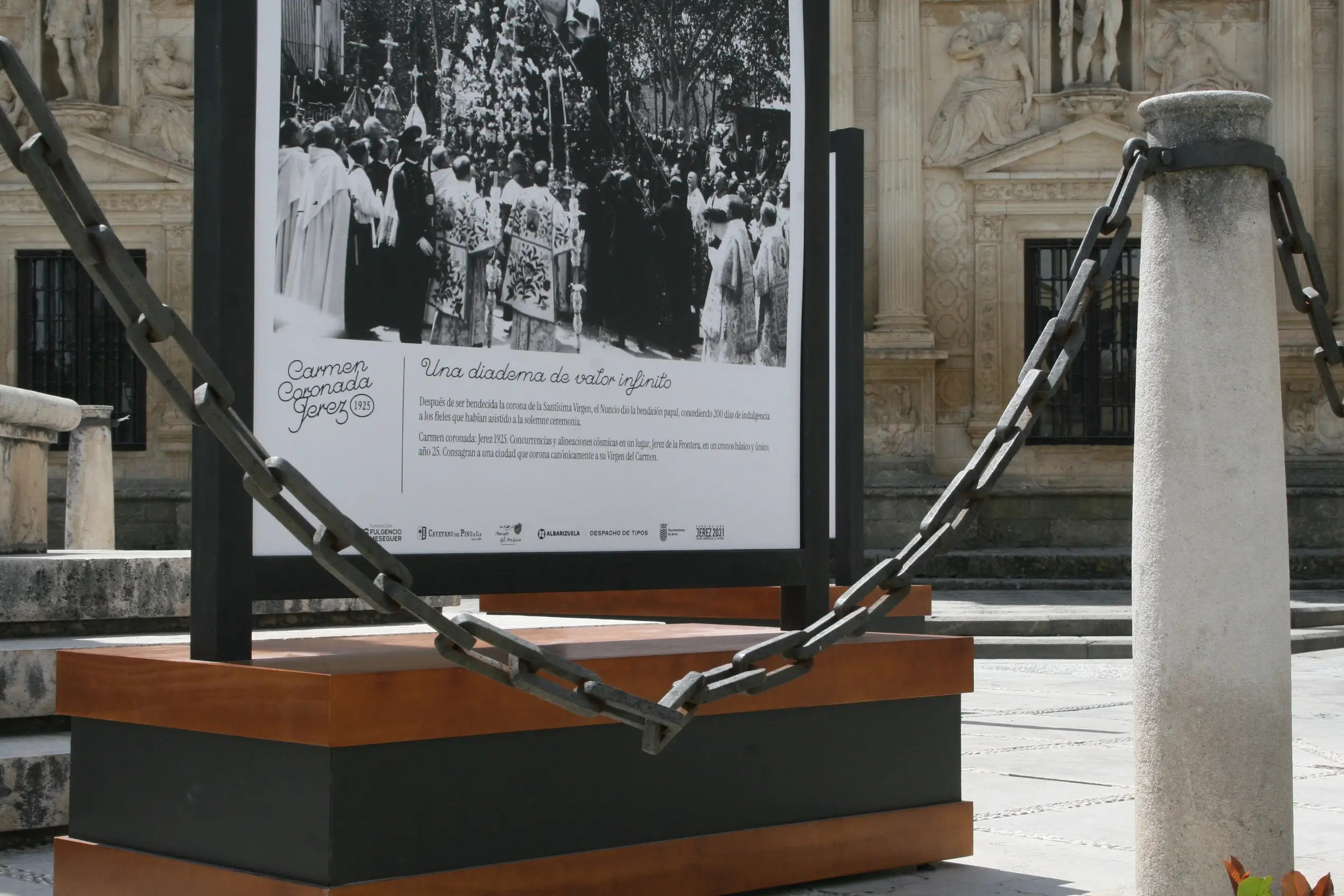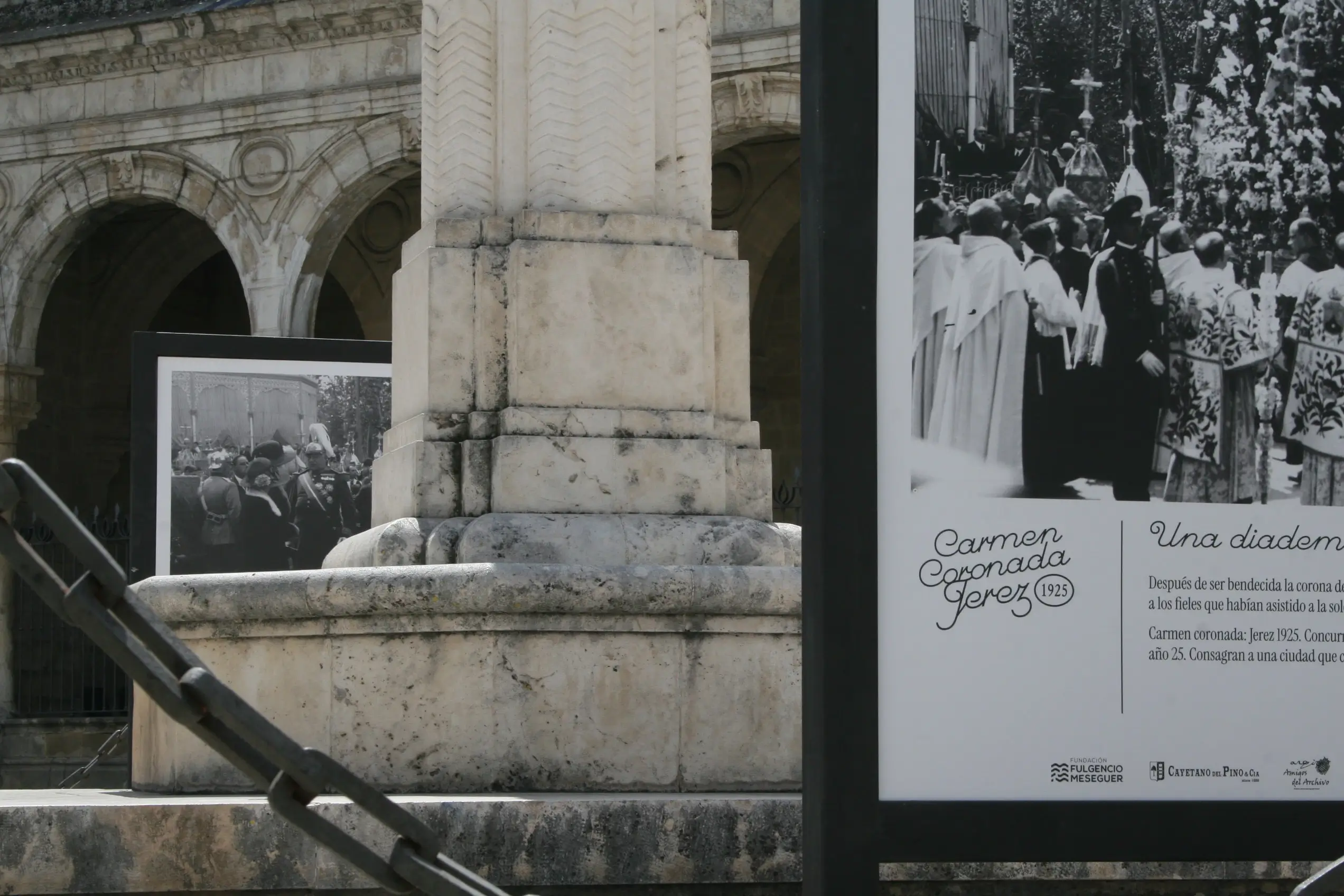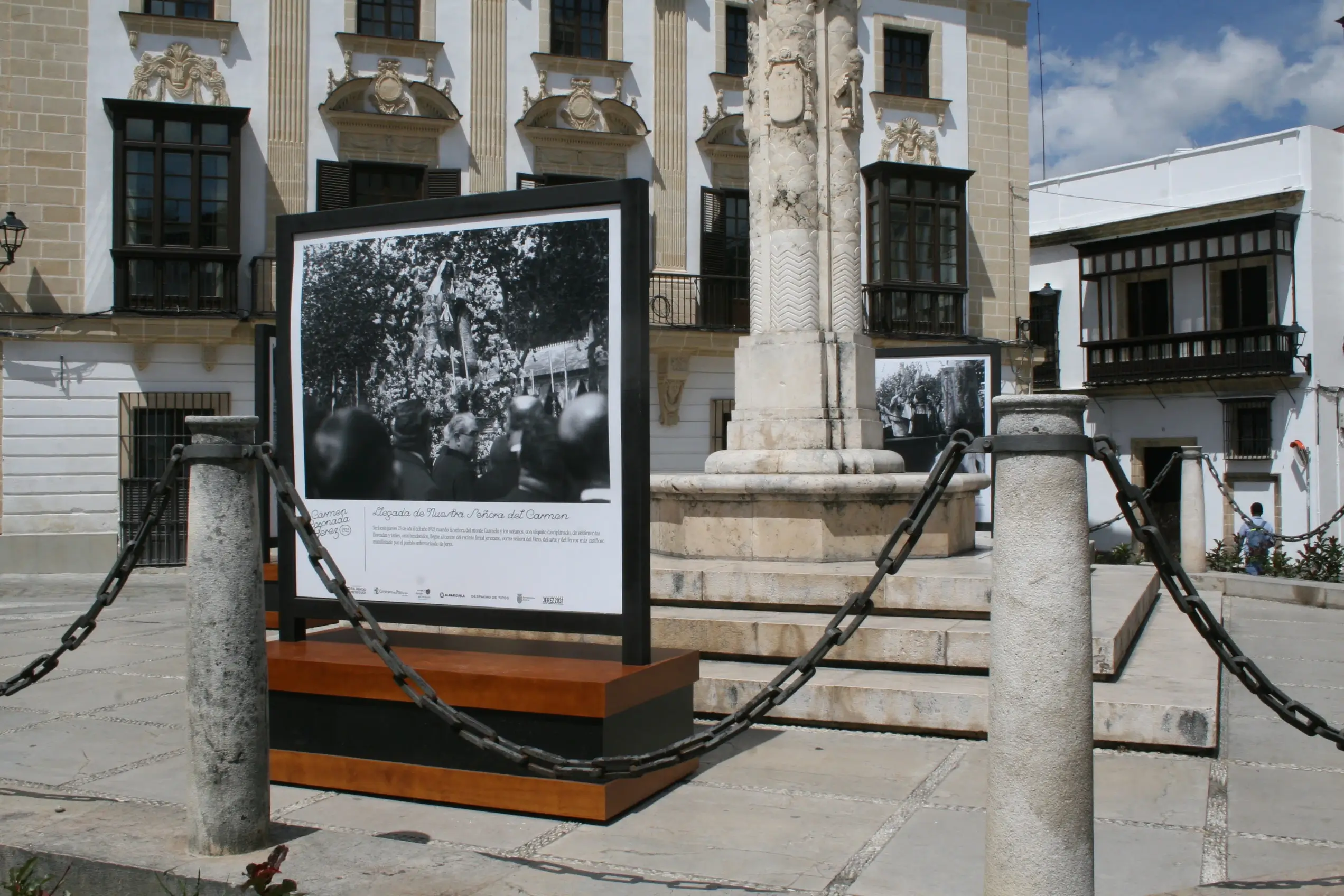
Tu fundición tipográfica local de confianza. Despacho de Tipos es un proyecto documental cuya base formal reside en el archivo. A partir de esa investigación, rescatamos, analizamos y convertimos cada pieza gráfica en alfabetos completos. De este modo, ponemos estos rescates a disposición de cualquier jerezano o amante del patrimonio gráfico de nuestra ciudad.